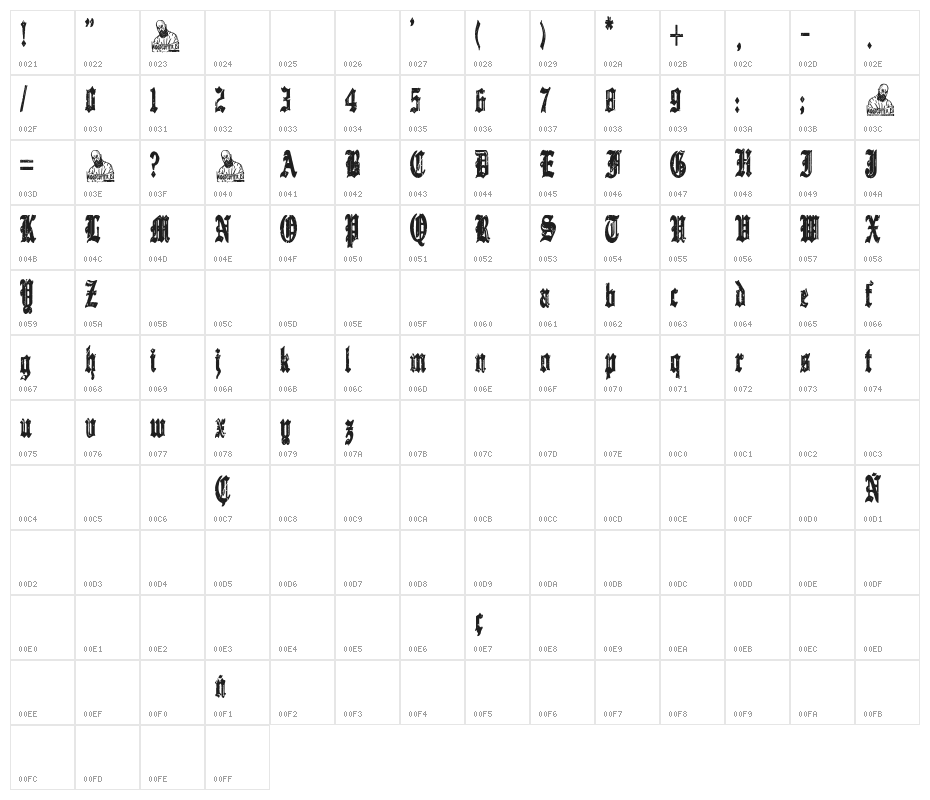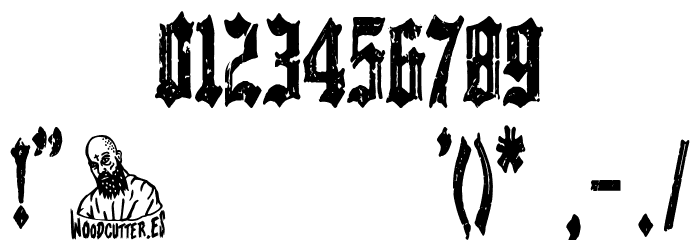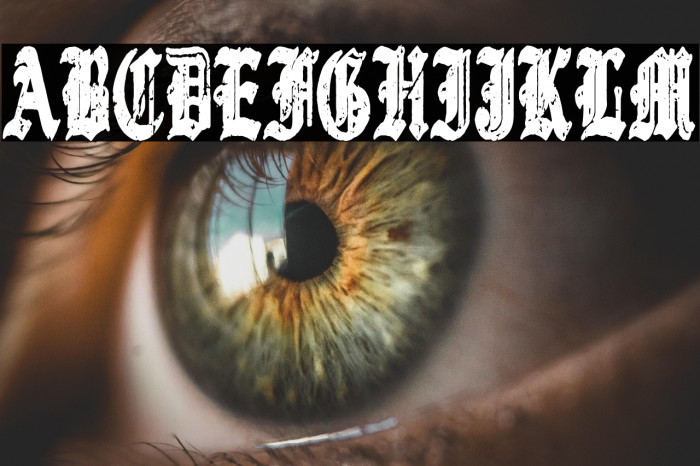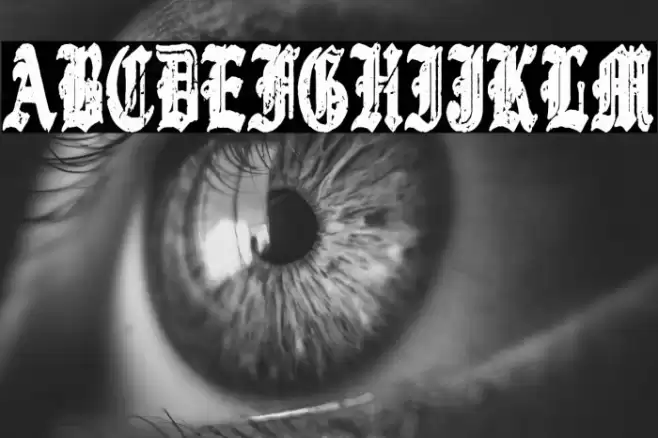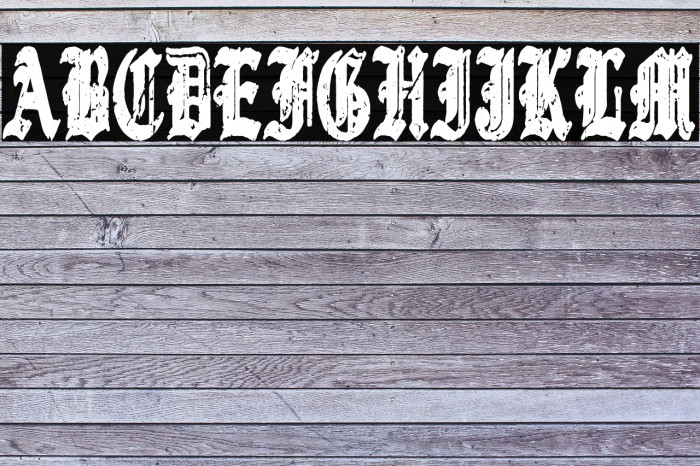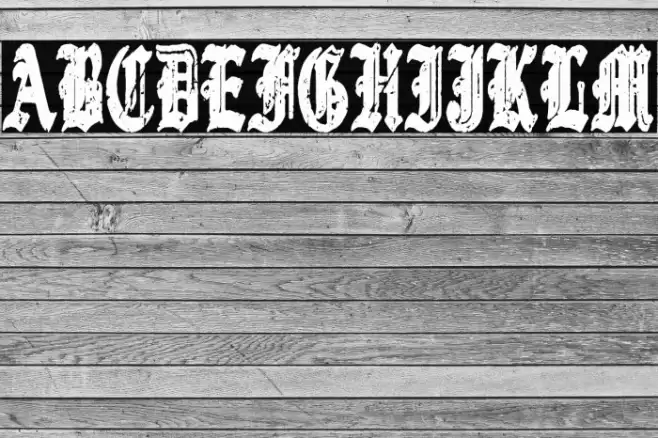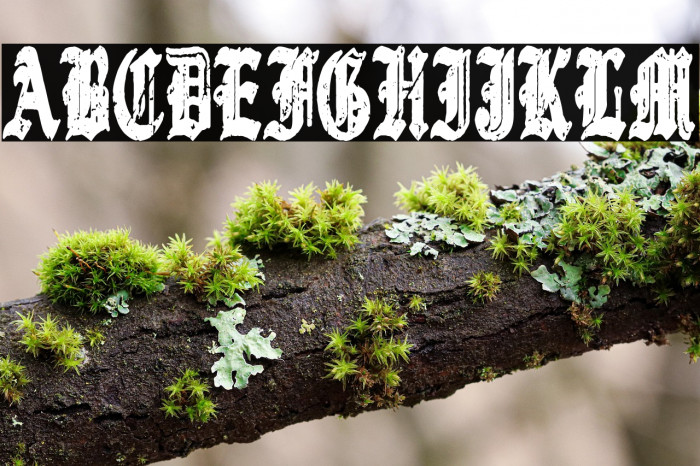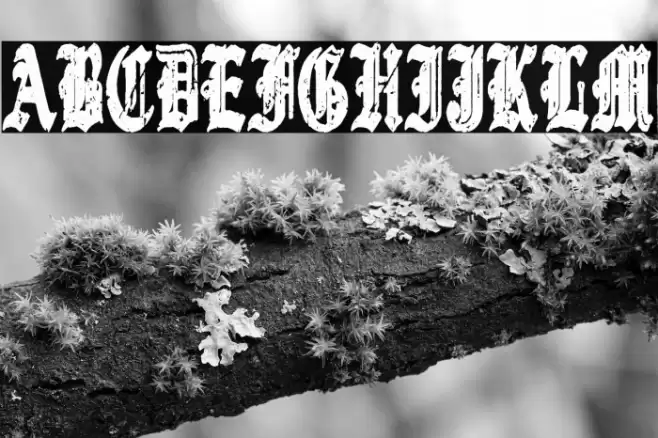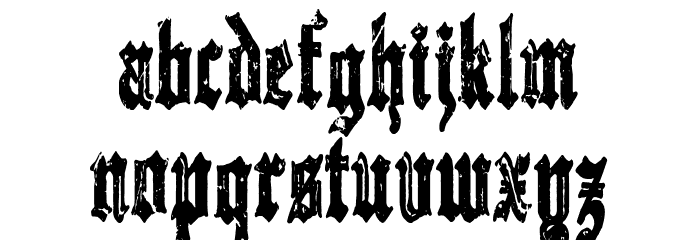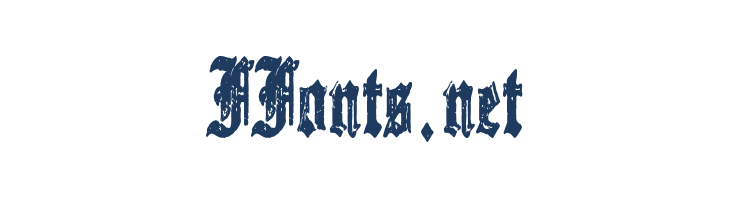
Gothic Destroyer Font
| カテゴリ | Gothic |
| 全体的なスタイル | Vintage, Decorative |
| おすすめプロジェクト | Ideal for fantasy-themed designs, vintage graphics, posters, and branding that requires a dramatic, historical feel. |